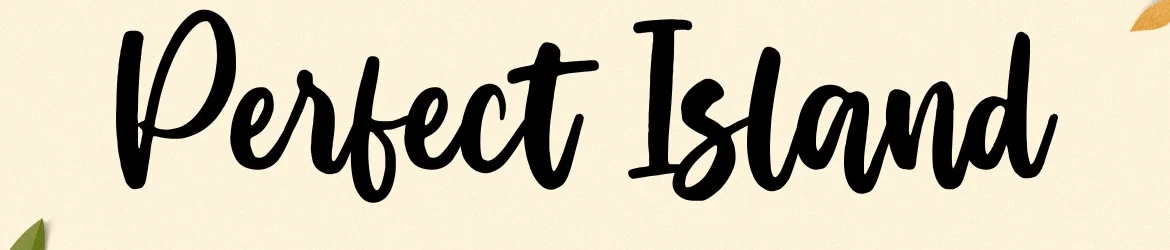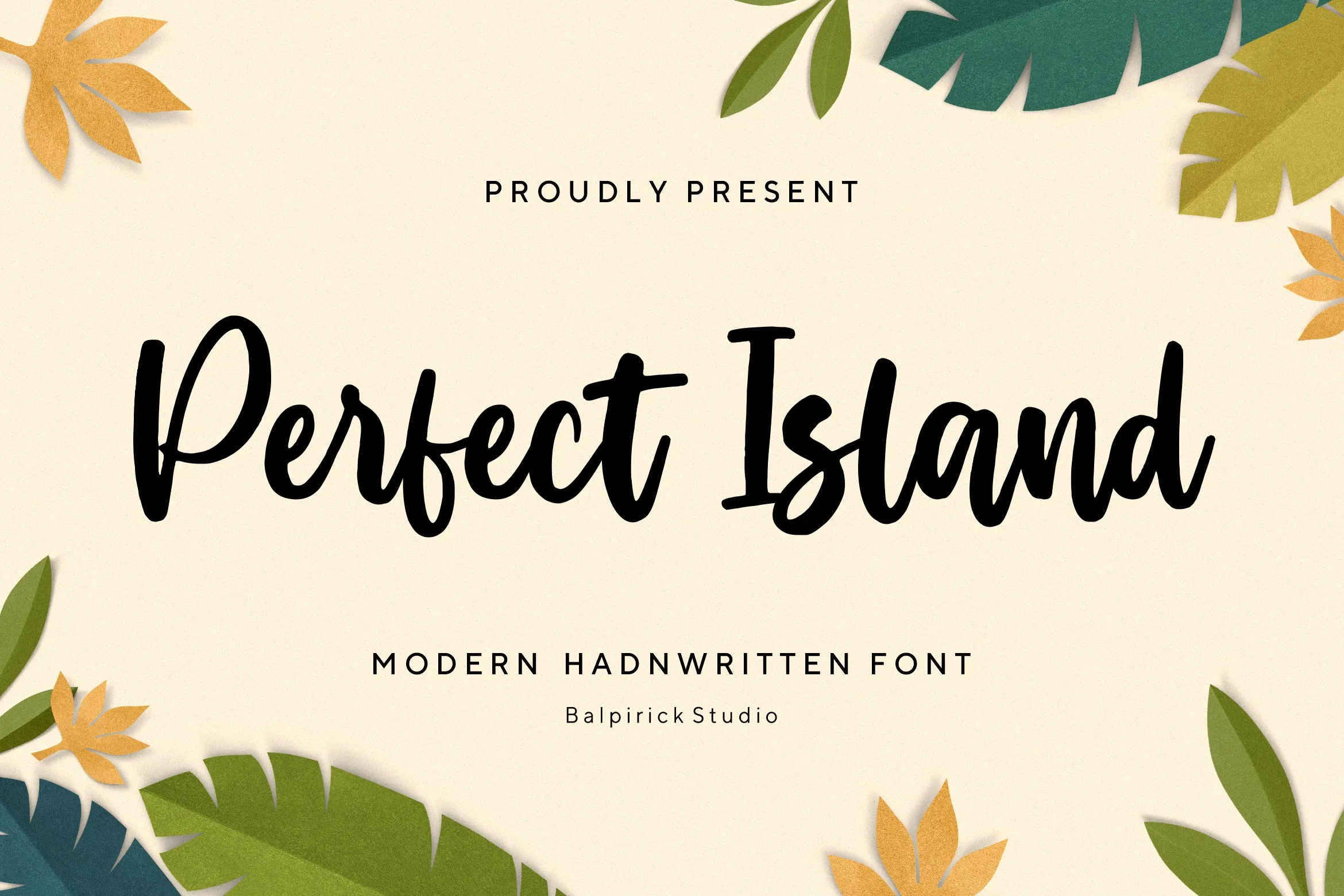
Perfect Island Font – Fonte Grátis
Perfect Island Font
A fonte ‘Perfect Island Font’ é uma seleção perfeita para quem busca adicionar um toque delicado à sua criação visual. Inspirada no estilo do caligrafista, essa fonte escrita a mão apresenta caracteres encantadores e divertidos que parecem dançar harmoniosamente sobre o nível de base. Suas linhas suaves e traços finos criam um sentido único e emocionante para qualquer projeto, tornando-o ainda mais especial. Seja um cartão de visita personalizado ou uma capa de livro exclusivo, ‘Perfect Island Font’ é a fonte perfeita para transformar seus conceitos em realidade visual. Adicione esta font à sua coleção se desejar dar um toque sofisticado e único aos seus materiais digitais.